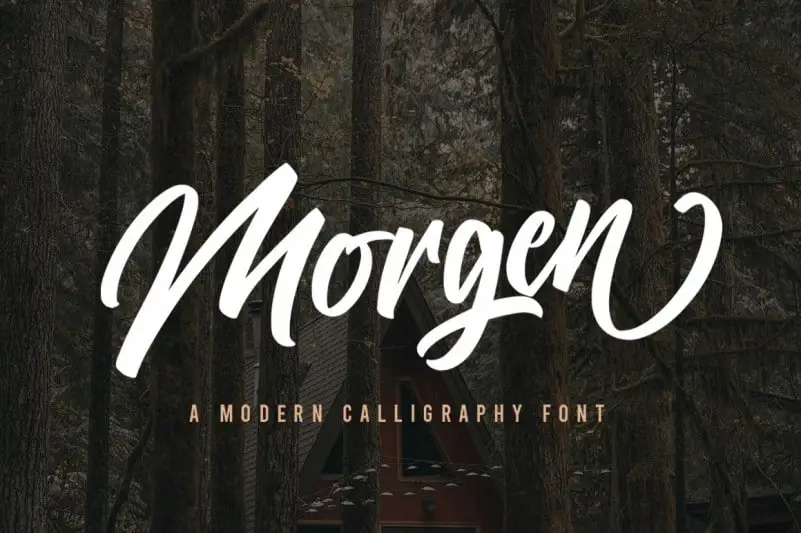
Descubra a Morgen Brush Font no seu próximo projeto criativo. Esta elegante e robusta tipografia foi especialmente projetada para designers que procuram uma solução única e sofisticada. Com suas linhas grossas e arredondadas, o Morgen Brush traz um toque distinto às criações mais originais. Seja para logotipos, posters ou editoriais digitais, esta font se destaca por sua facilidade de uso e personalização. Observará como as ideias que você tem em mente ganham vida nas suas obras com o Morgen Brush Font. Experimente uma versão experimental agora e veja como ele pode revolucionar seu design.